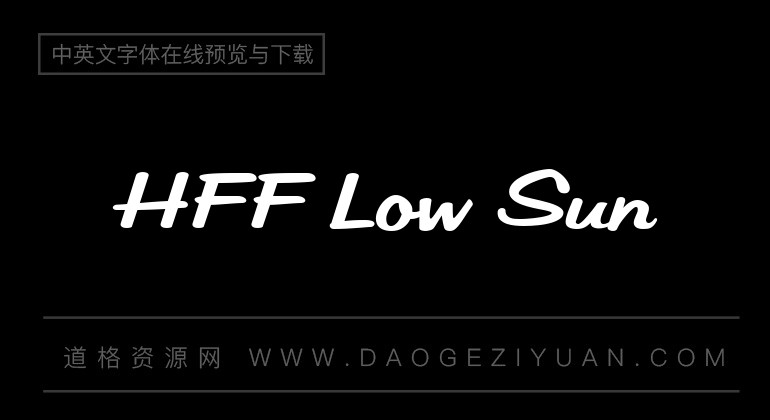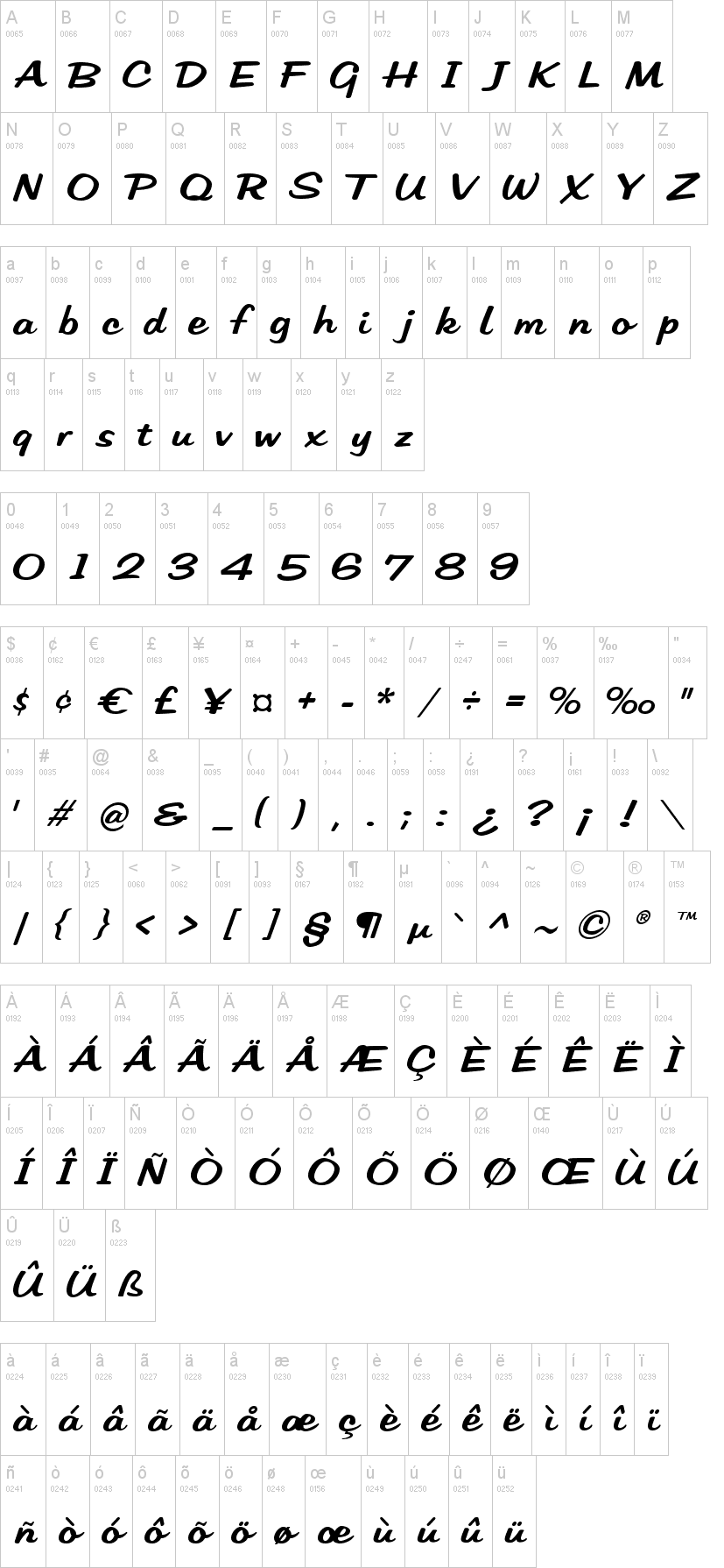
HFF Low Sun
? HFF Low Sun 字体是由HFF国际字体工作室设计的一款现代技术字体。它采用了现代的技术,使字体的细节更加精细,更有质感,更具有表现力。它的特点是字体的细节更加精细,更有质感,更具有表现力,而且可以在低像素环境下使用,可以满足多种设计需求。
HFF Low Sun是一款非常不错的手写艺术字体,具有很好的视觉感,适合于文化类的宣传设计、商业类品牌的广告和产品包装设计以及个性化文字排版等较多场景。